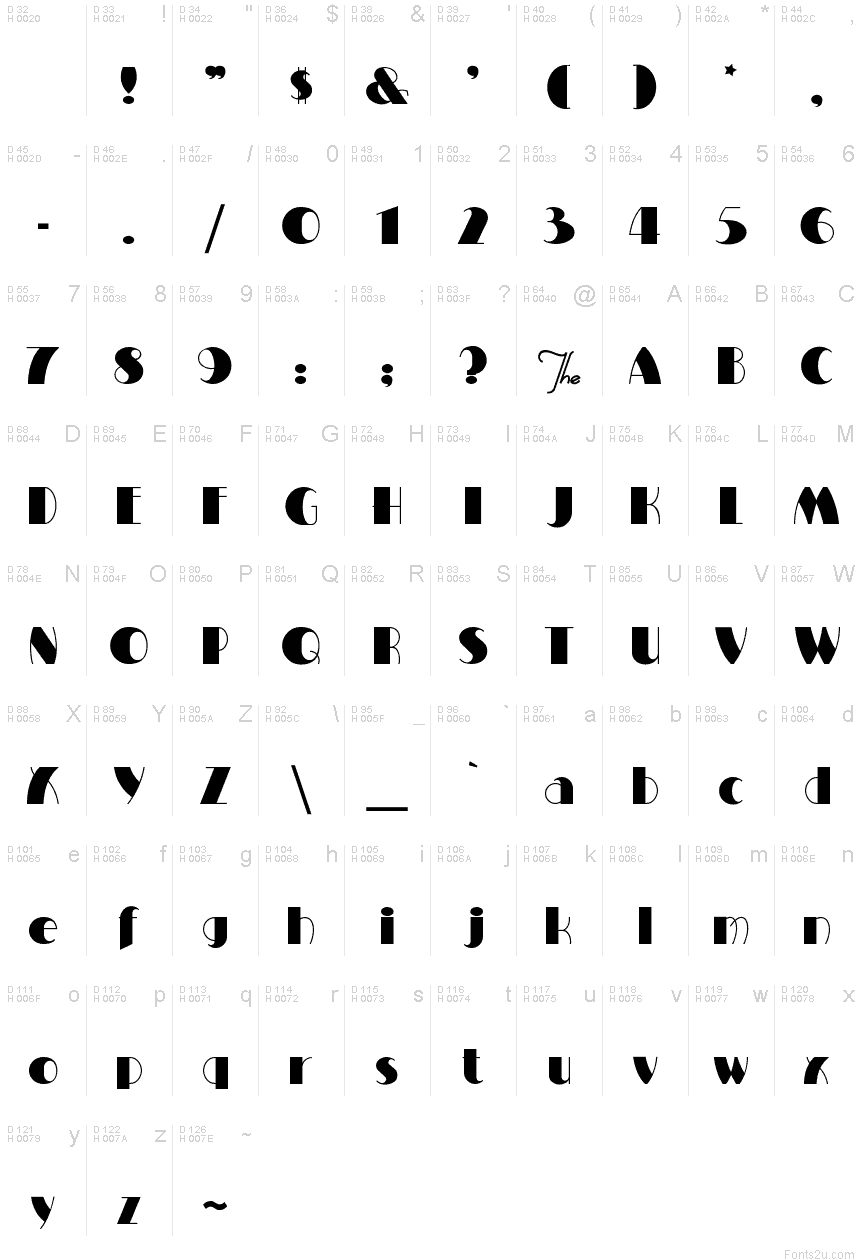
Milton Burlesque autorstwa Nicka Curtisa to bezpłatny, retro font displayowy o zaokrąglonych, plakatowych kształtach i rytmie inspirowanym estetyką burleski. Litery łączą szerokie łuki z płaskimi, kwadratowymi cięciami, co nadaje im charakter szyldów reklamowych bez zbędnych ozdobników.
Milton Burlesque świetnie sprawdzi się na plakatach eventowych w stylu vintage, w tytułach kabaretowych, ulotkach teatralnych, logotypach i opakowaniach, które wymagają nawiązania do rozrywki XX wieku. Proste kształty i teatralne krzywizny sprawiają, że idealnie nadaje się do krótkich nagłówków – zwłaszcza gdy chcesz, aby nazwa lub tytuł niosły ze sobą energię dawnych scen.